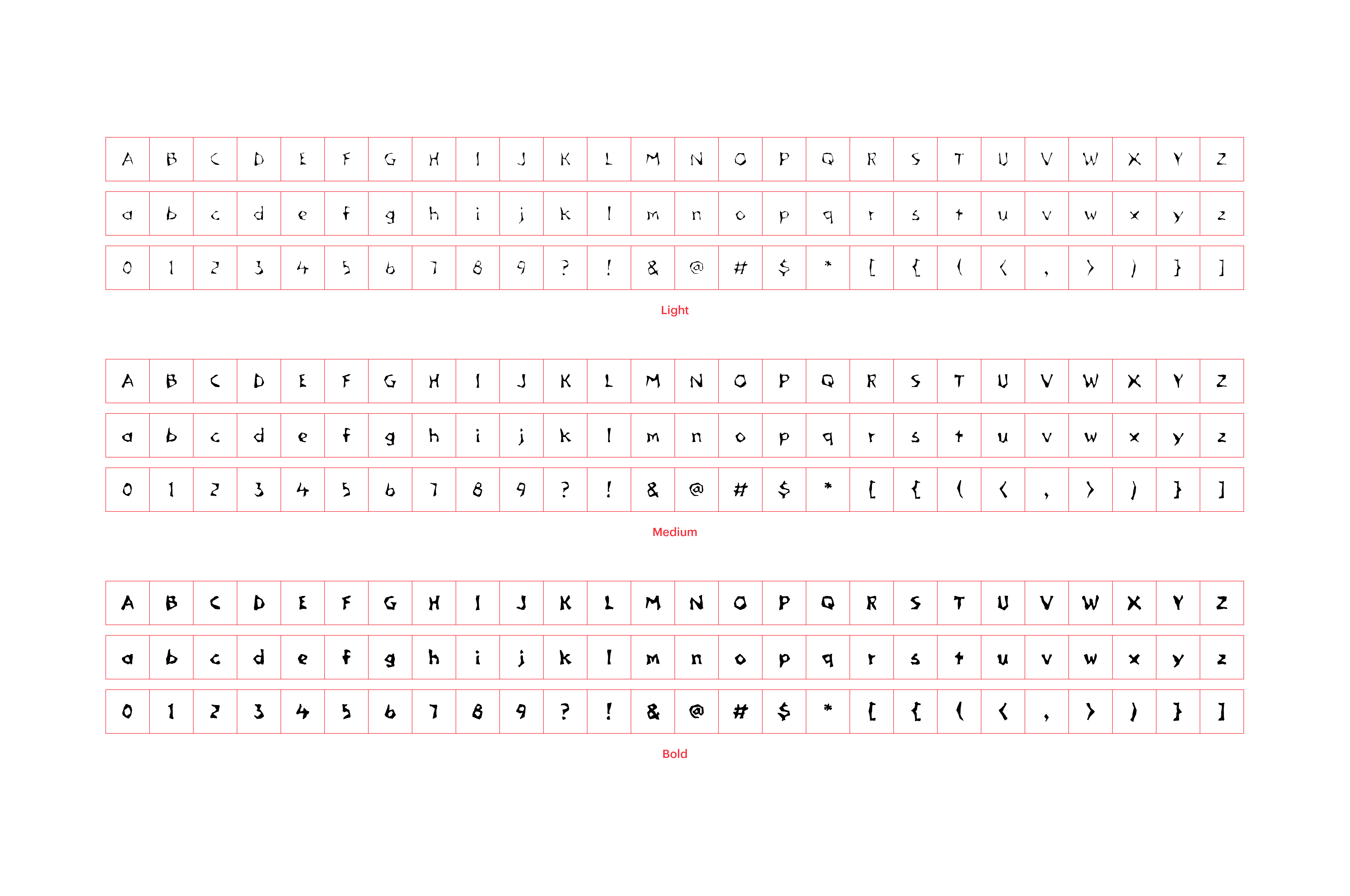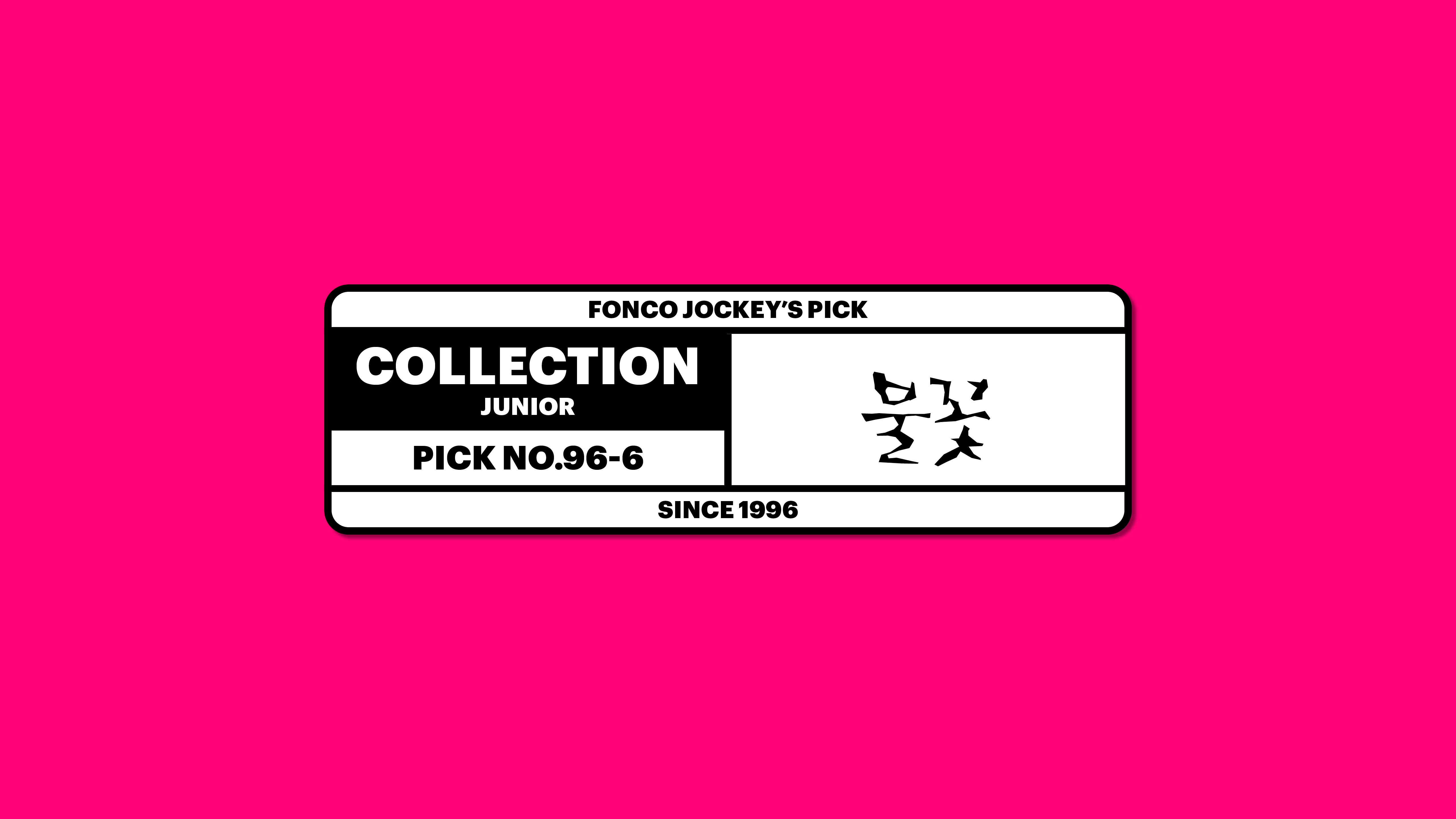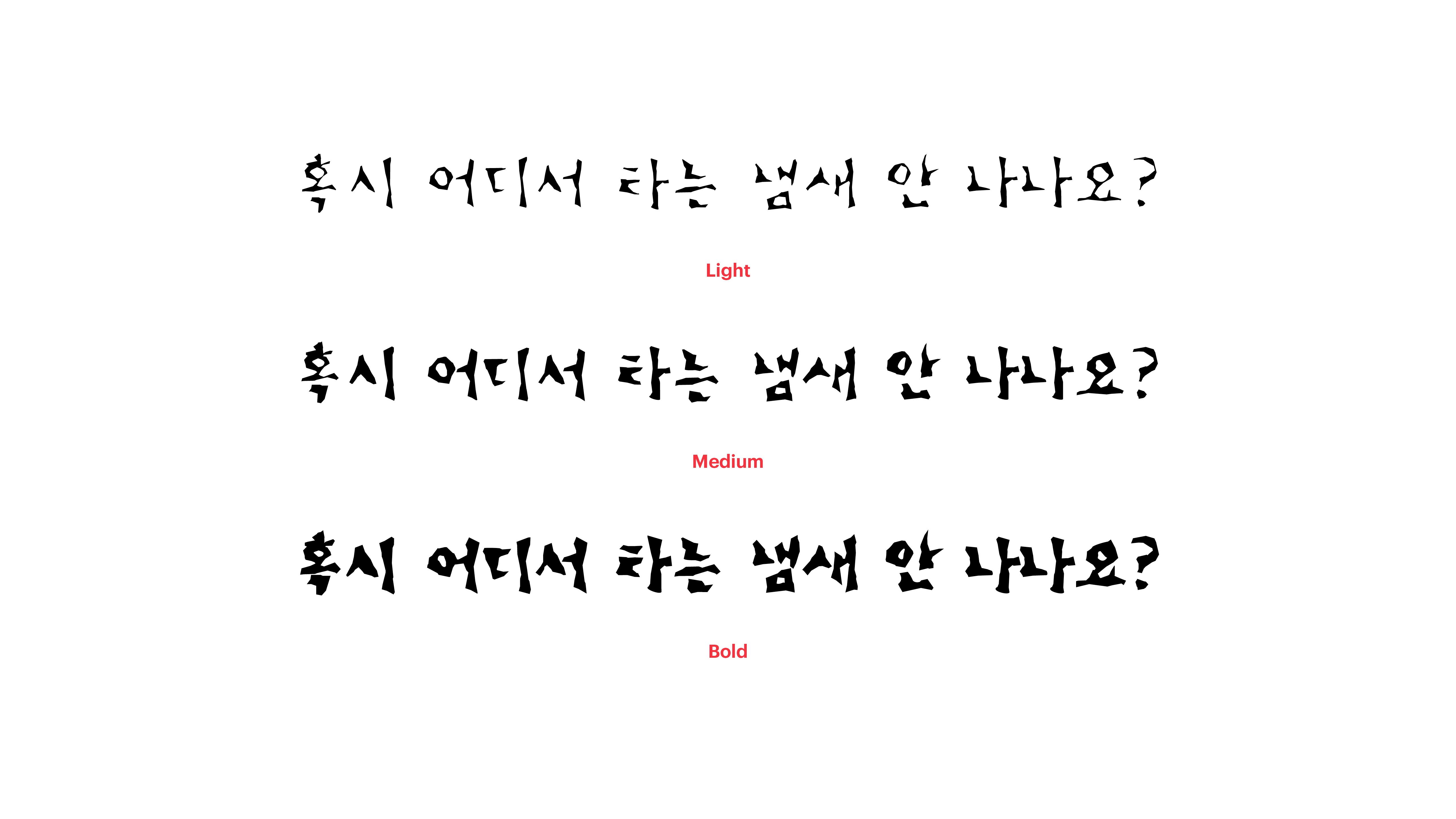
불꽃
Yoon 불꽃
불꽃체는 글자의 조형성보다는 감성적 표현에 집중한 새로운 스타일의 감성 폰트입니다. 곡선보다는 직선을 주로 사용했으며, 선의 강약 또한 정해진 방식에 구애받지 않고 자유롭게 표현해보았습니다. 앗, 여러분, 그런데 혹시 어디서 타는 냄새 안 나나요? 시도 때도 없이 불타오르는 불꽃체의 이 열정을 어쩌면 좋죠?